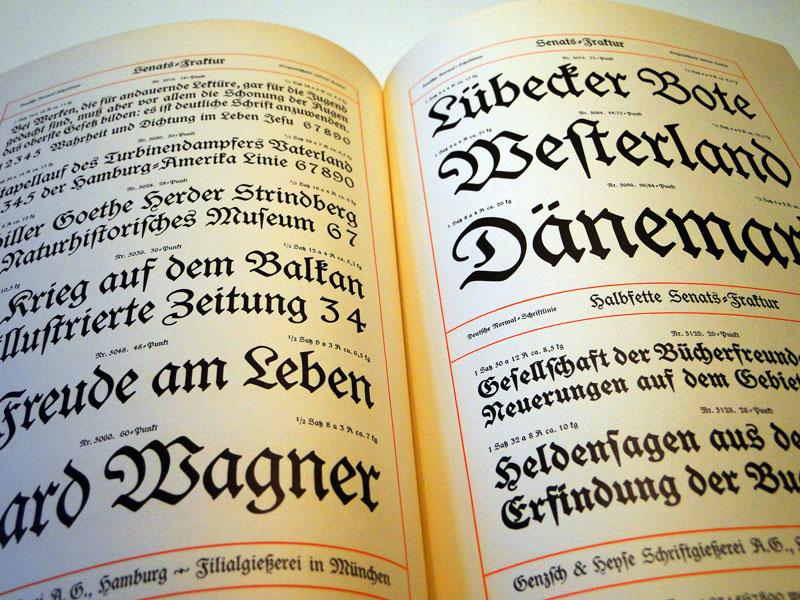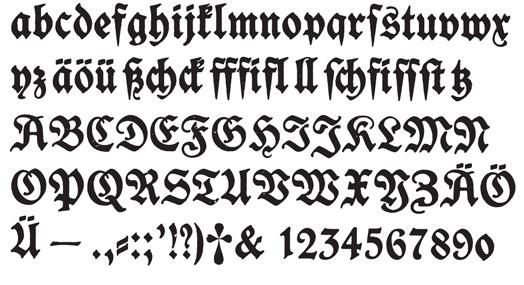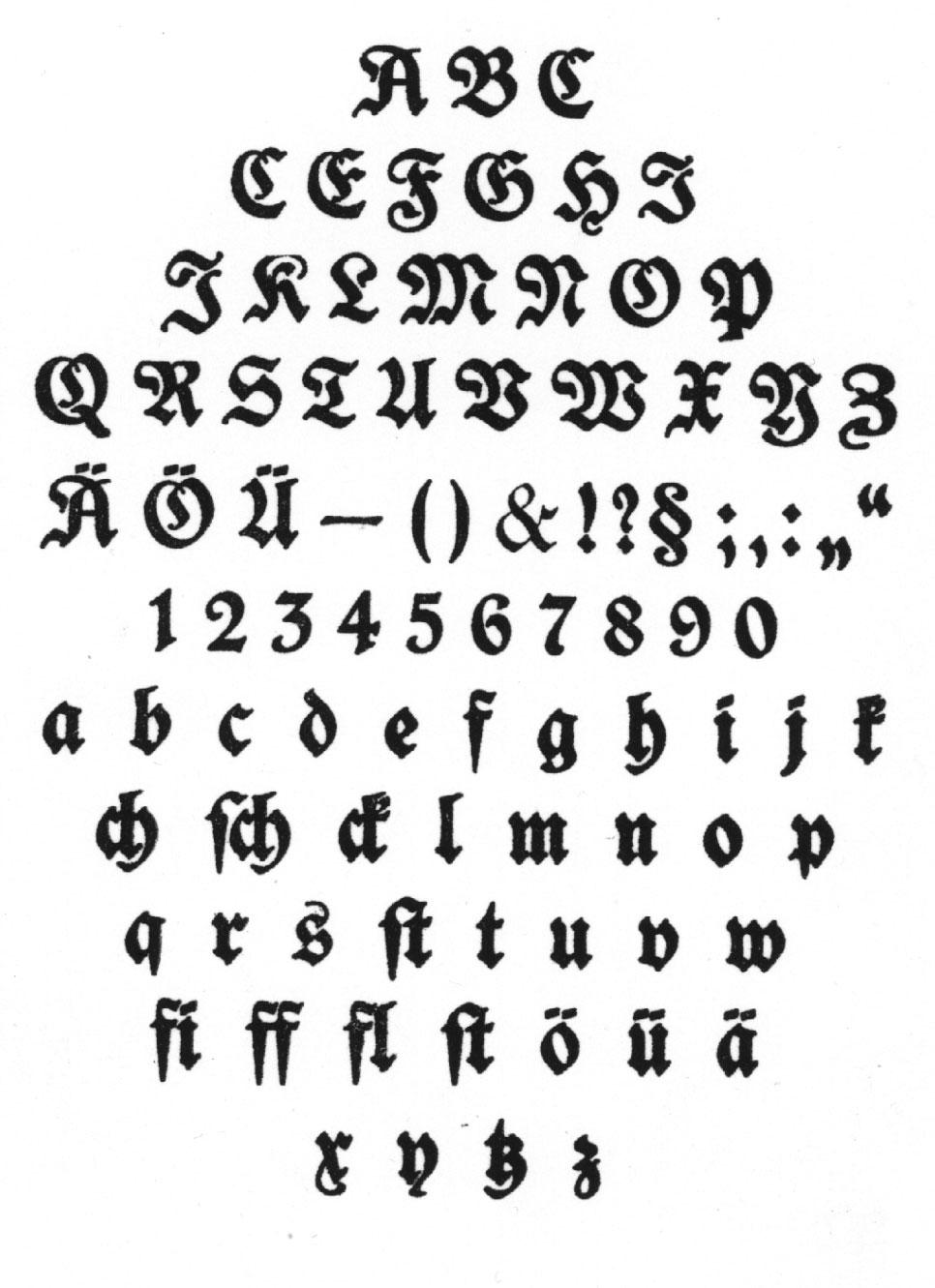
Mir unbekannte Bleisatz-Fraktur
Ich würde gern wissen, wie diese wirklich hübsche Fraktur heißt und aus welcher Gießerei sie stammt. Hab alle meine Schriftmuster durchgeschaut, aber nirgendwo dieses A gefunden, was mir am Charakteristischsten zu sein scheint, weil ich so etwas vermutlich noch nie bewußt gesehen habe. Ich kenne mich allerdings mit Frakturschriften auch nicht so gut aus. Die Schrift ist Komplettguß und stammt aus einer Druckerei in Nordostdeutschland ... könnte also aus einer Berliner oder Hamburger Gießerei stammen, muss aber nicht. Danke für die Hilfe!
P.S.: Die ist so schön, läuft auch prima lesbar in kleinen Graden ... gibts die eigentlich auch brauch- und bezahlbar digital?